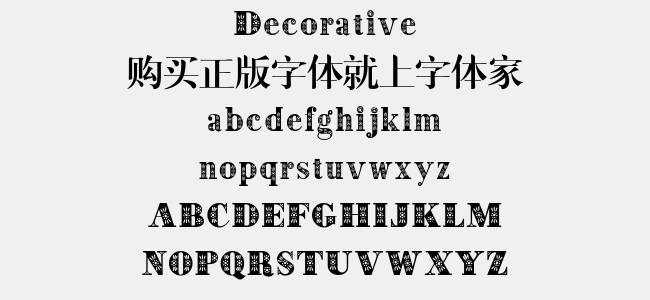
Decorative
字体作者:现代字体
字体名称:Decorative
字体字数:26个英文大小写字母及和阿拉伯数字
字体家族:未知
书体类型:英文类
字体公司:未知
Decorative
该字体是一款个性独特的英文字体,非常适合创意类的PS字体,英文广告设计载体上使用,在设计中选择这款字体应用的话,会起到非常理想的效果。